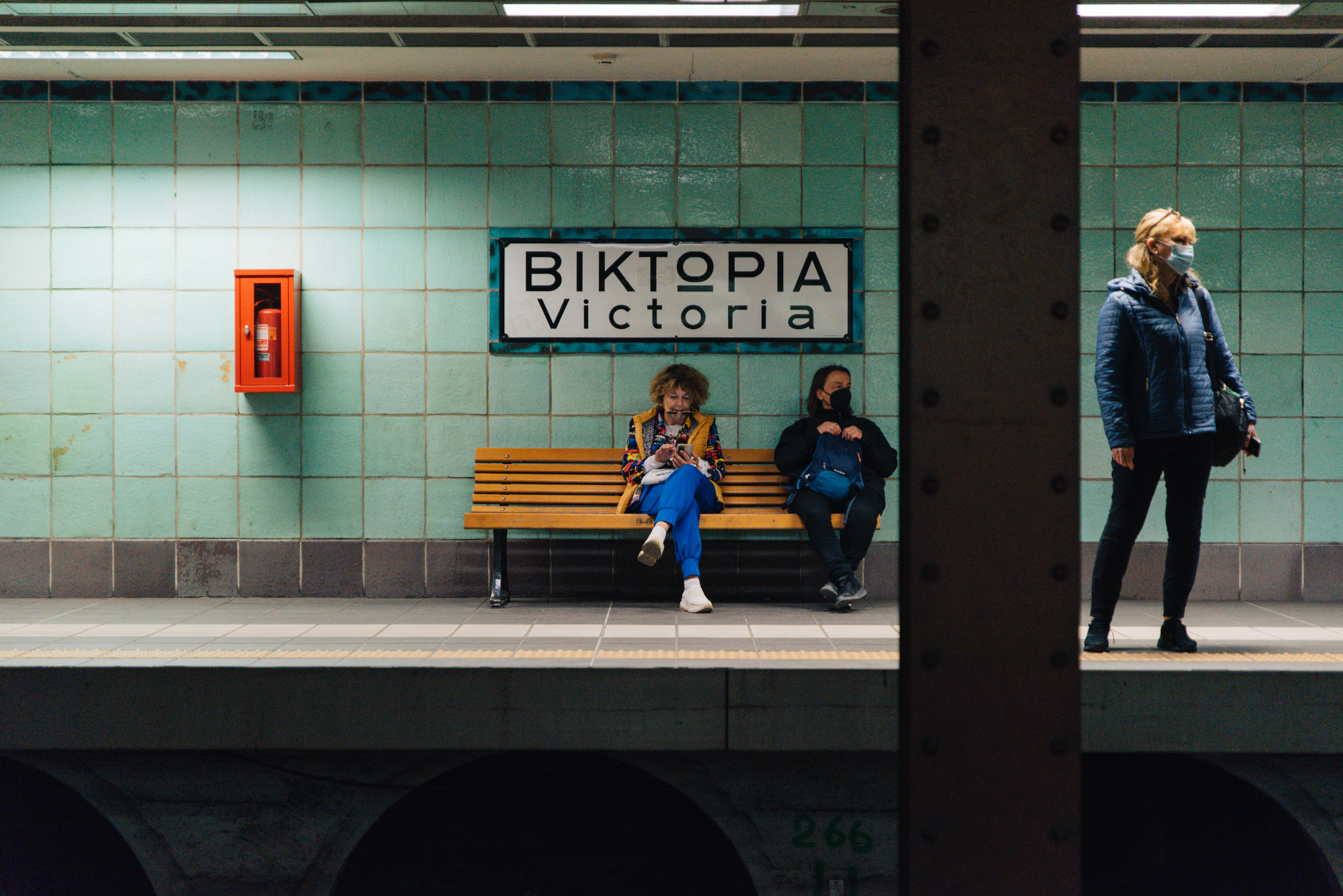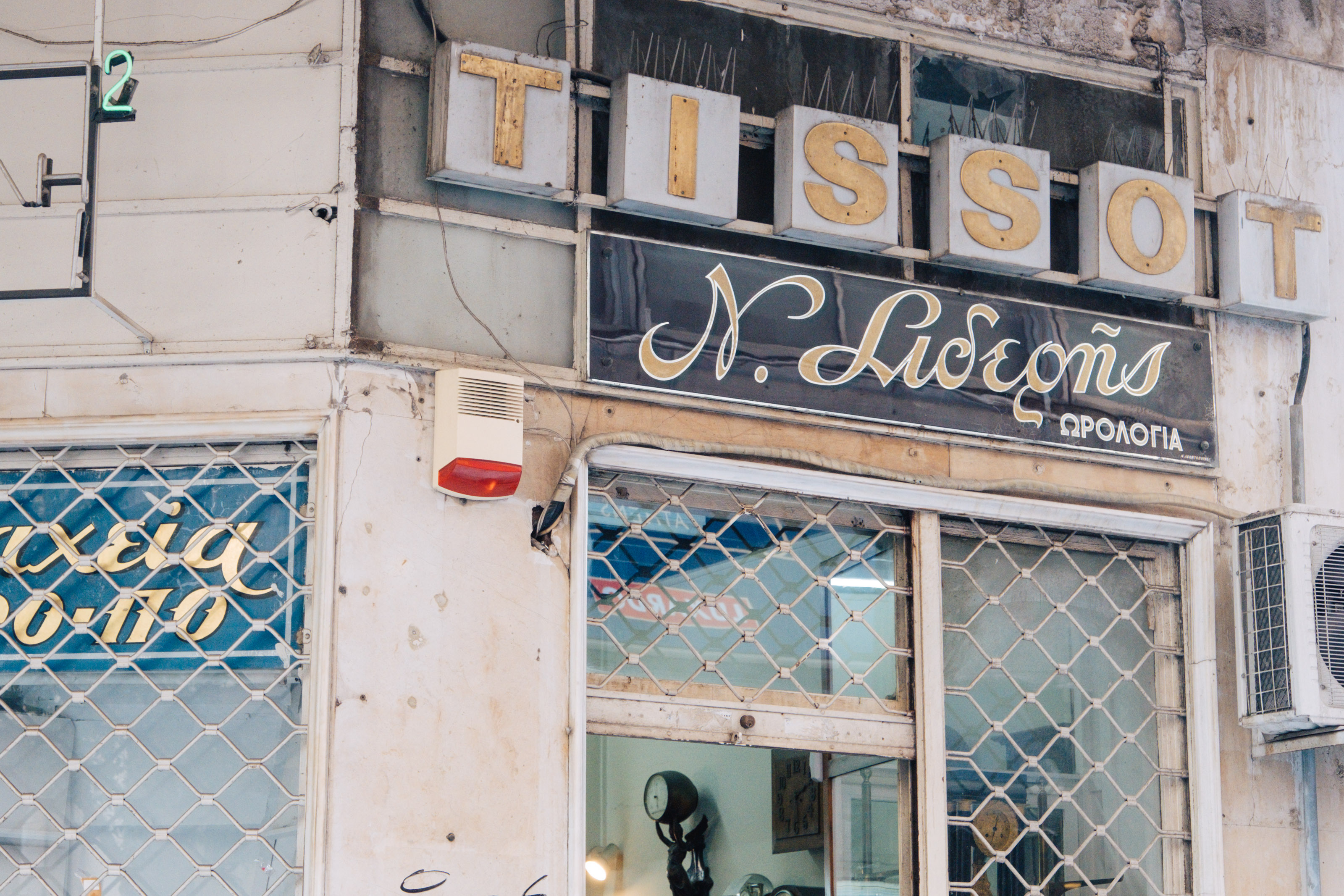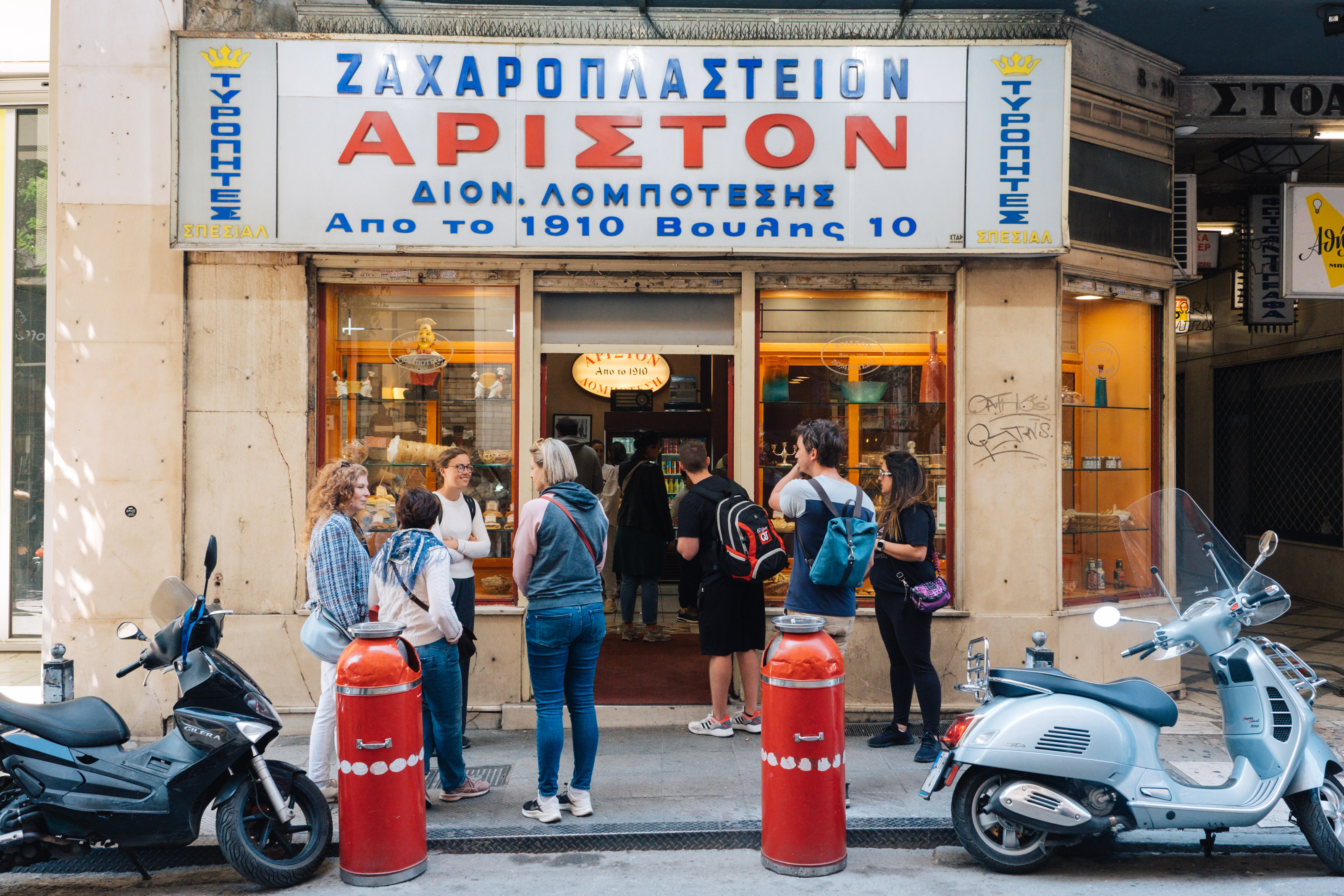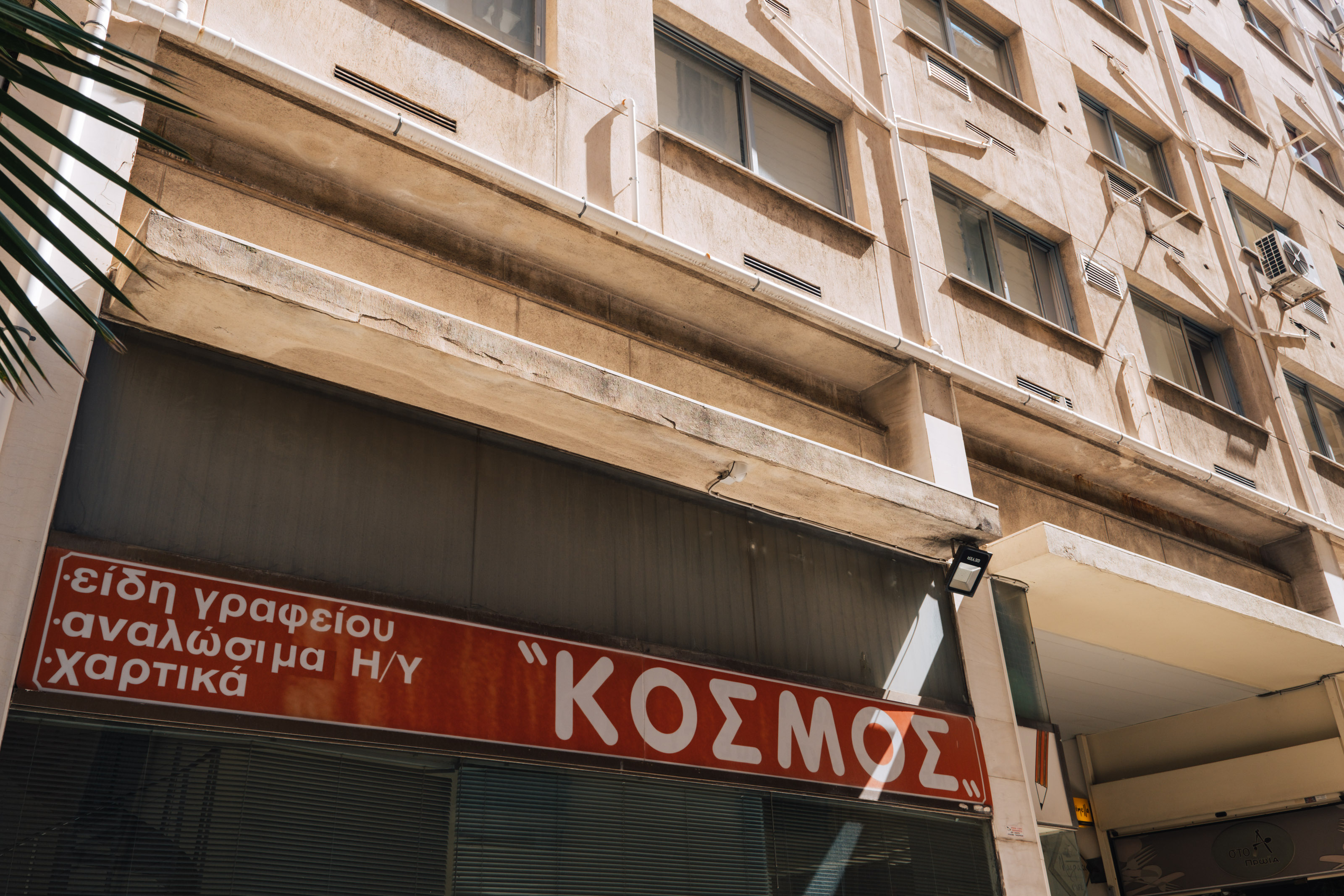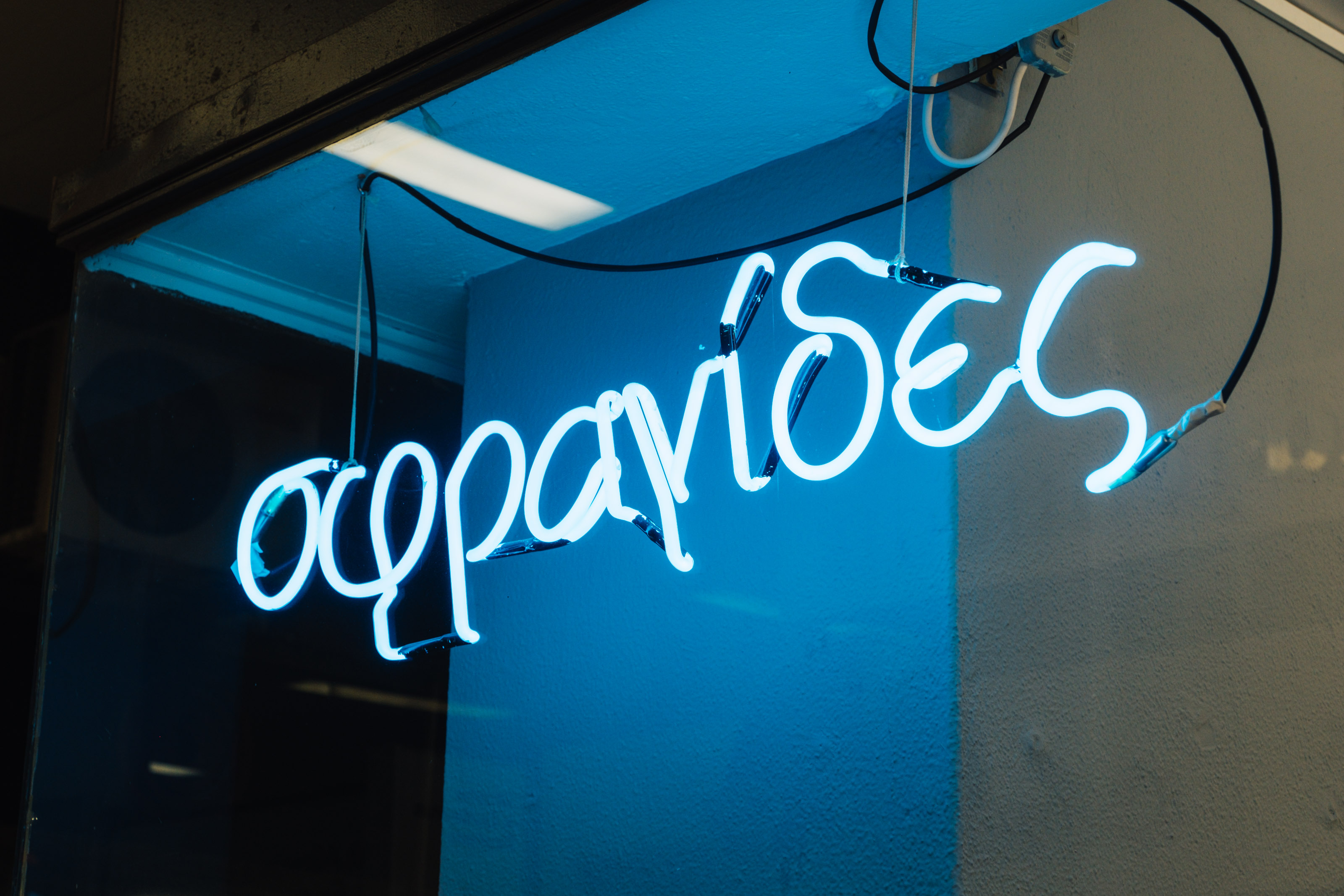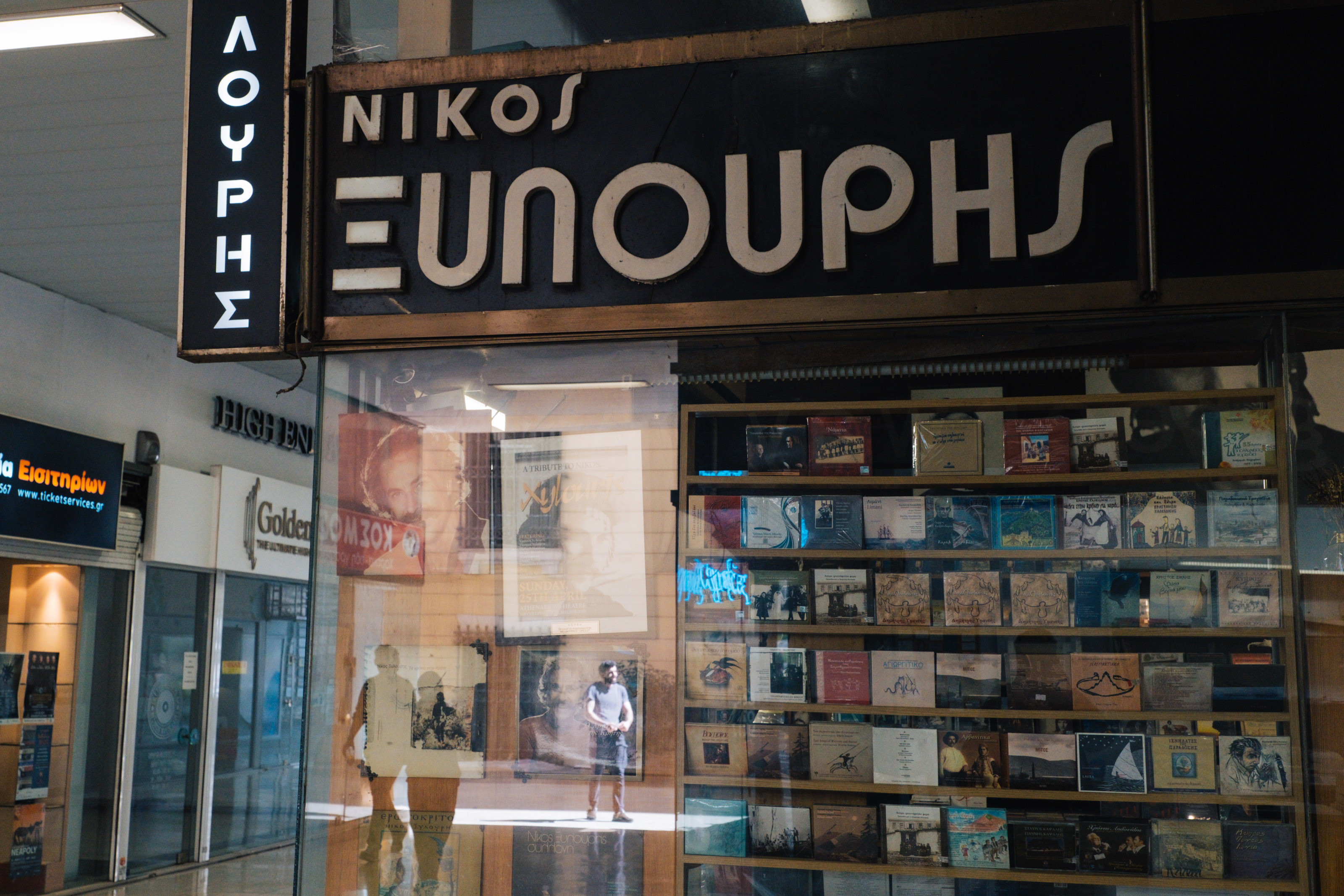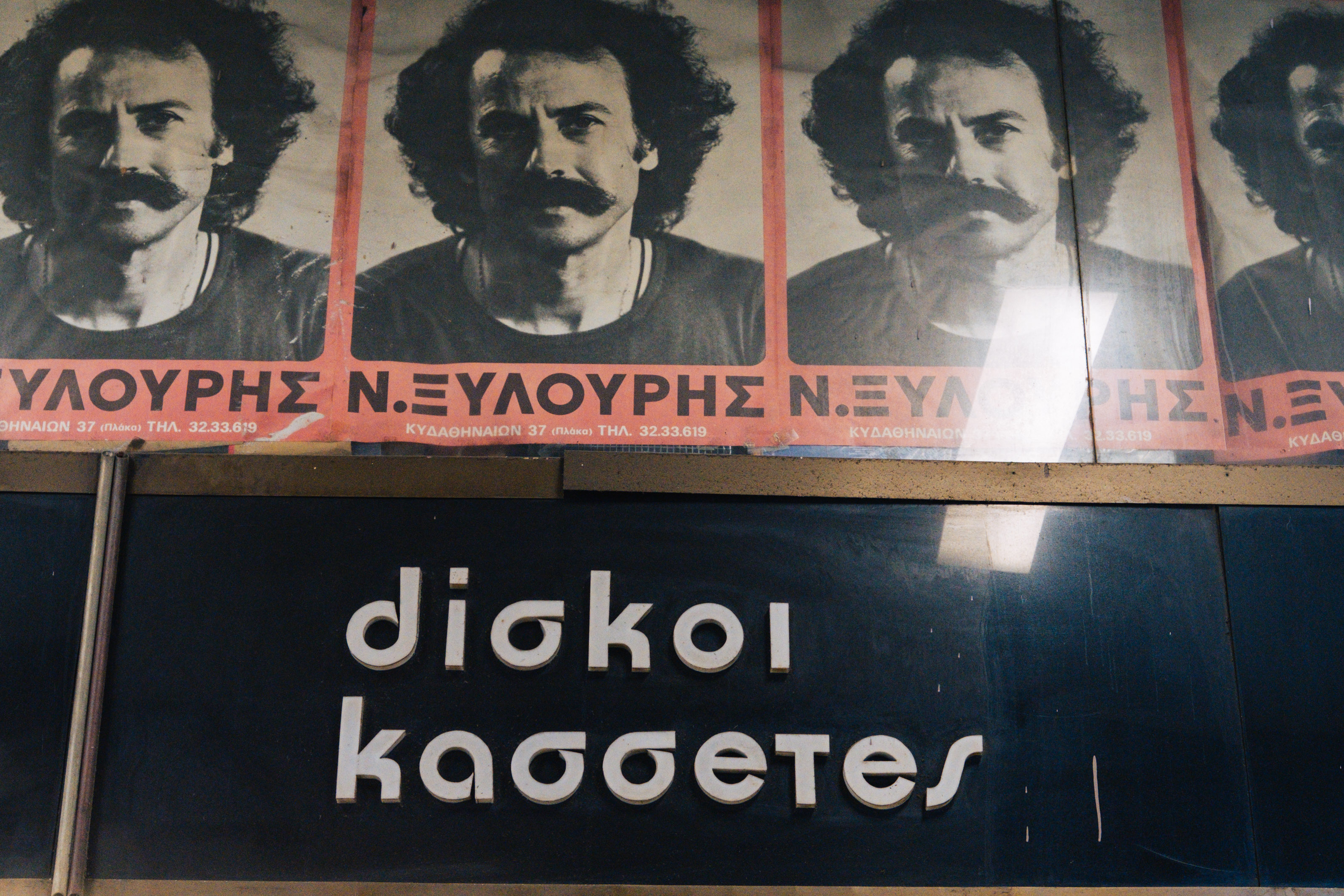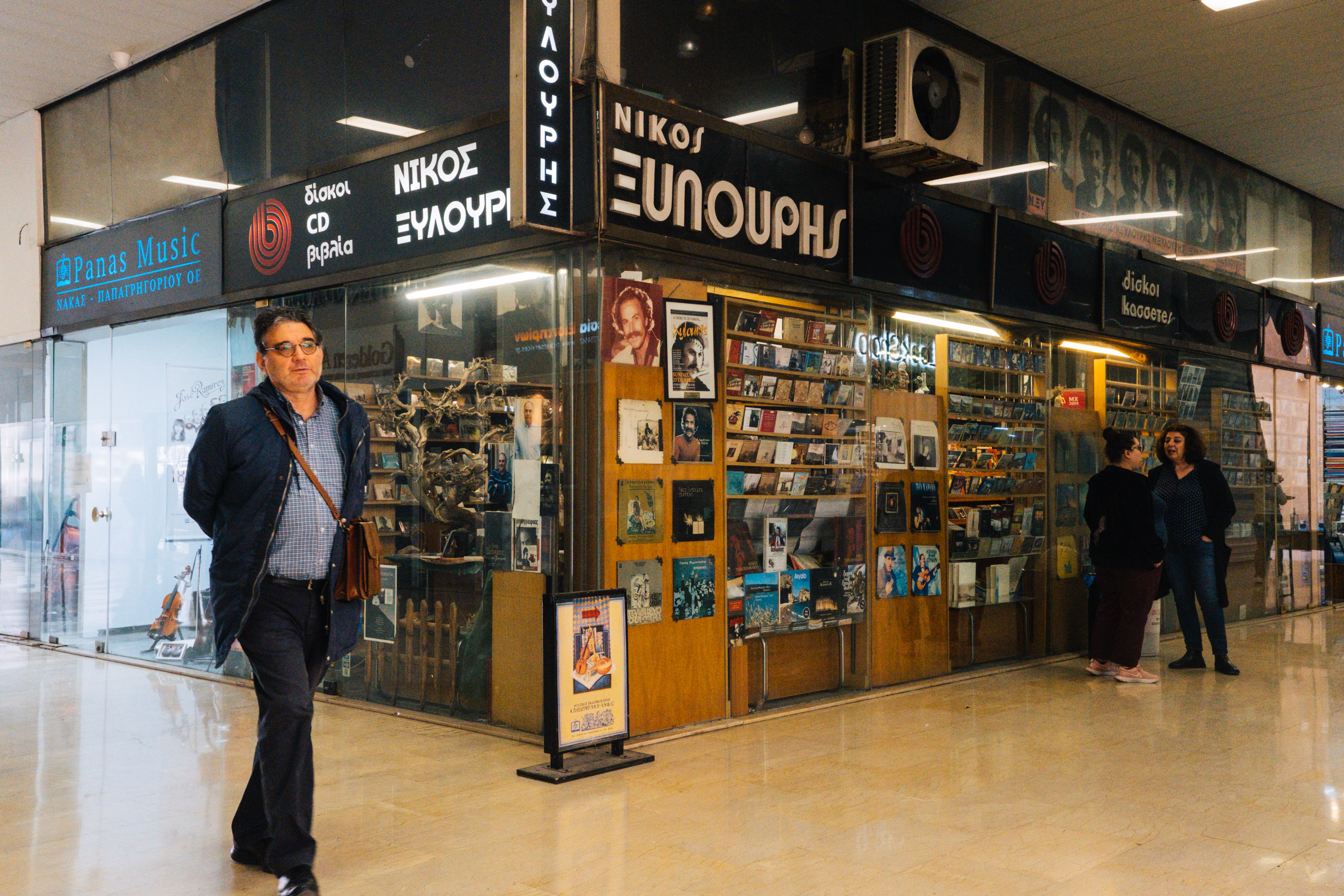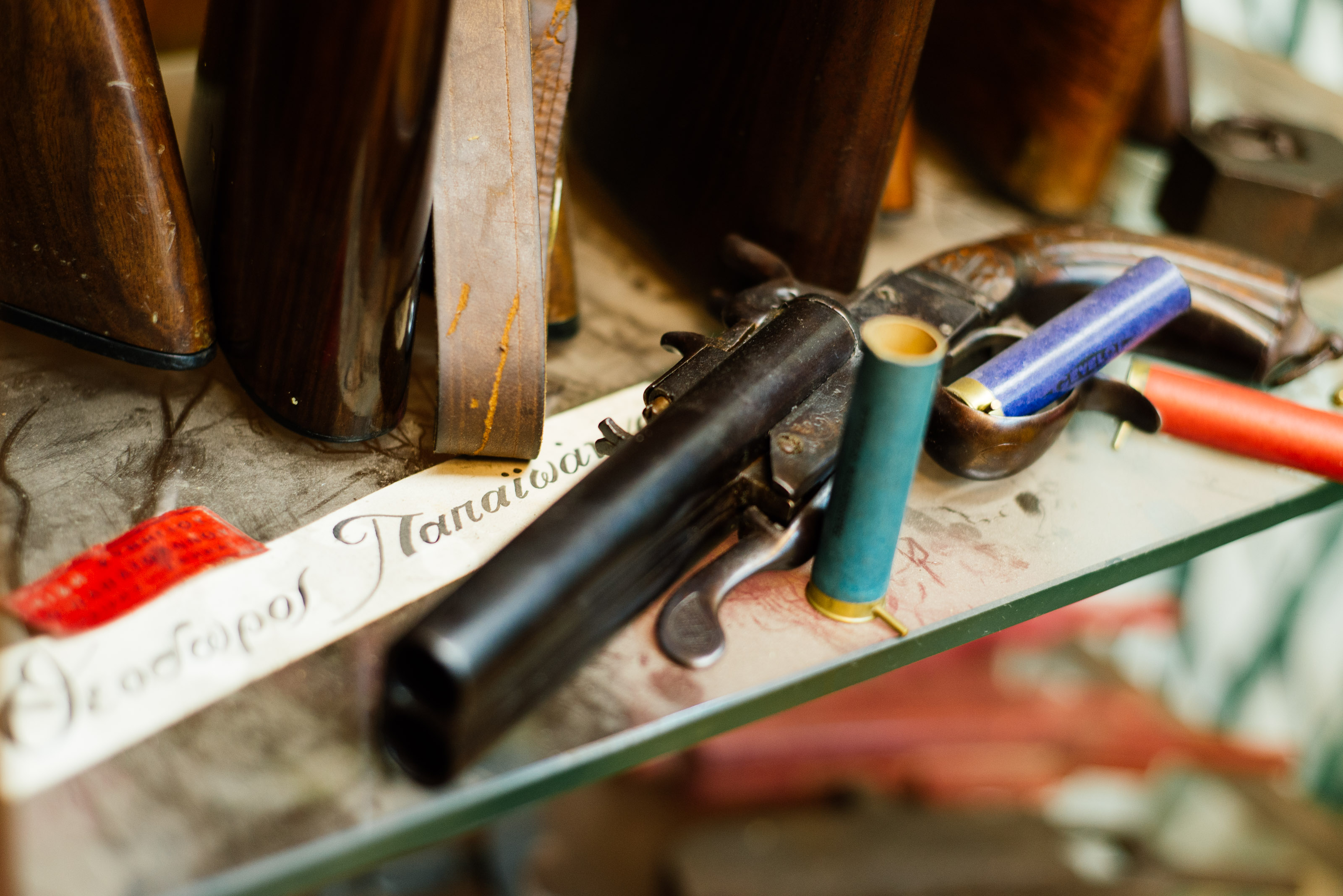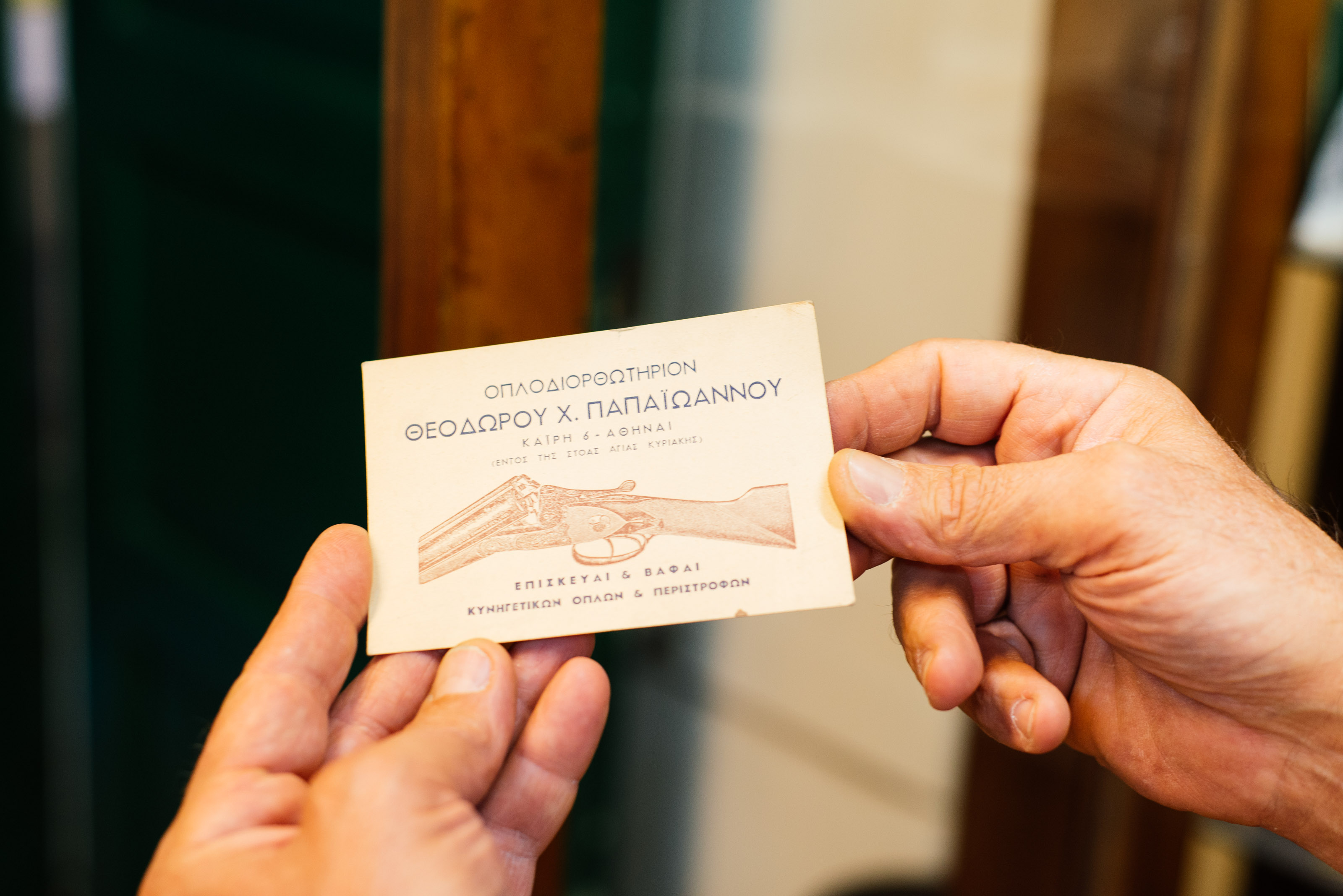
Die Verlegerin und Typografielehrerin Natassa Pappa führt uns durch das grafische Ökosystem Athens und schlüsselt das Kleingedruckte auf, das es zu etwas Besonderem macht.
Athen Typ
Die Schönheiten
Die Schriftdesigner Panayotis Haratzopoulos und Yannis Karlopoulos, die Fonts.gr 1995 gründeten, initiierten zusammen mit Vassilis Georgiou das Stella-Projekt, das "ein Versuch war, die vergessene Kunst der griechischen Kalligrafie zu studieren, die von den 50er bis in die 70er Jahre blühte". Durch das Studium von Schildern, Anzeigen, Umschlägen und Verpackungen der Vergangenheit digitalisierten und modernisierten sie Briefe, die sonst verblasst wären.
...und die Biester
Folgen Sie den Schildern